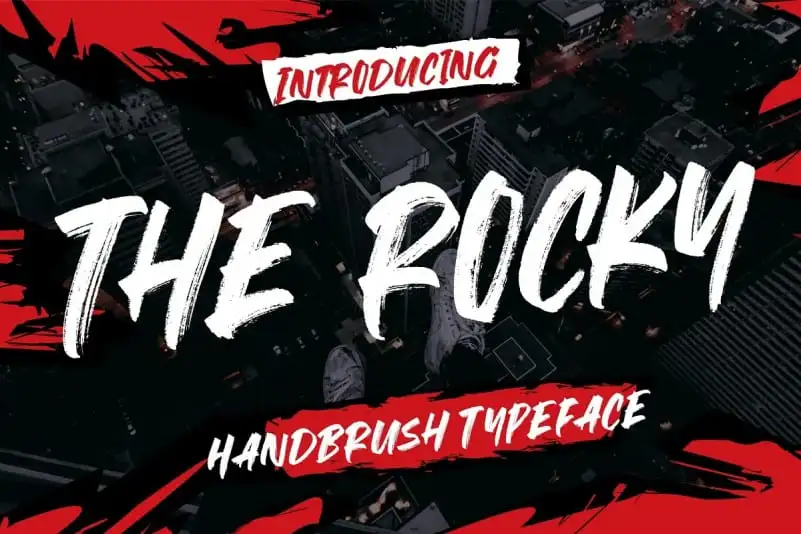
The Rocky Brush Font – Download Grátis
A fonte “The Rocky Brush Font” é uma escolha perfeita para designers que desejam adicionar um toque elegante e único aos seus projetos digitais, especialmente quando se trata de trabalhos que exigem uma aparente escrita à mão. Através do designer 99designs, oferecemos a você uma font exclusiva que combina uma escrita manuscrita com o poder das letras cursivas e dos traços brush. Seja para criar um logo inovador, adicionar personalidade aos designs de casamento ou produzir etiquetas sofisticadas, “The Rocky Brush Font” está pronta para oferecer a sua solução. Além disso, essa font é ideal para anúncios, embalagens de produtos e até mesmo para criar o famoso fundo d’água na fotografia, criando um efeito imersivo sem igual. Seja qual seja seu projeto — desde convites de casamento até materiais de escritório — “The Rocky Brush Font” não só oferece uma experiência visual única, mas também entrega profissionalismo para qualquer tipo de trabalho.